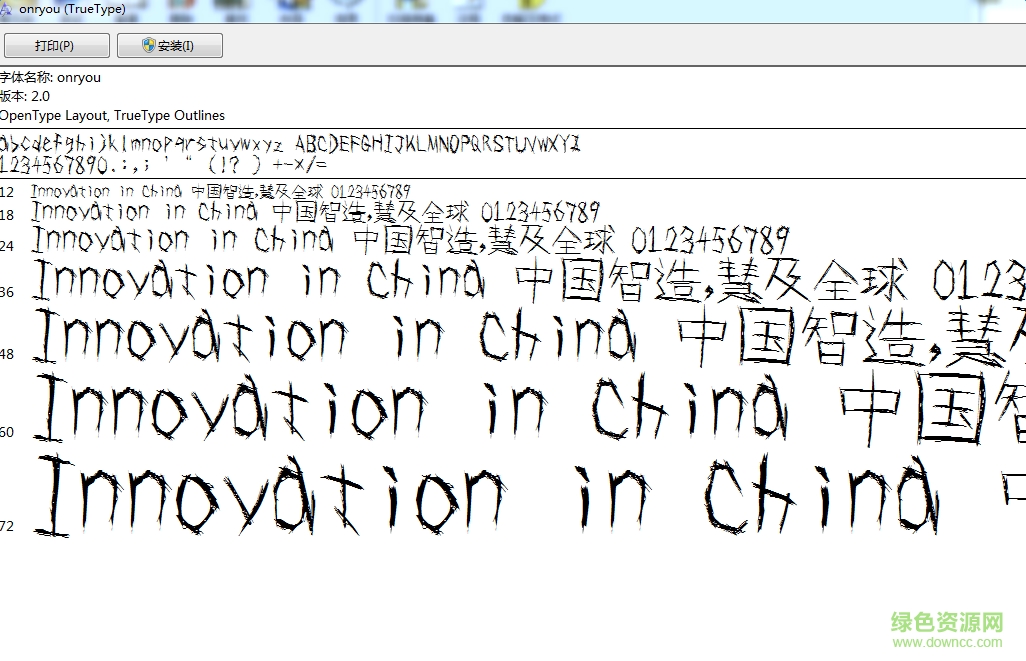
日本手写体怨霊字体是一款浪漫手写风格字体软件,怨霊手写体非常的非主流,字体笔画无拘无束,十分清新脱俗,整体效果别有一番韵味,还有更多好看字体欢迎来绿色资源网下载体验!
日本手写体怨霊字体是一款应用于艺术设计方面的简体中文字体,该字体笔画粗壮,尾部的甩尾有力且有丰富的笔触细节,大字效果突出且引人注目;并且最大程度还原作者书写字形,细节表现完整,且字库完整,可以广泛应用于名片设计、新闻媒体、宣传海报、ppt、影视制作以及内容用字等领域。
该字体笔画随意,每个字体用毛边突出,给人非常时尚非主流的感觉,非常适合装逼哦!